Особенности производства западноевропейской книги в Средние века. Письмо. Шрифт
Из предыдущих статей цикла «Особенности производства книги в Средние века» мы узнали о начальных этапах работы над рукописью: выделке пергамента, подготовке красок, выборе количества тетрадей, размера будущей книги и композиционного решения листа. Когда всё это было сделано, начиналась работа по заполнению страниц текстом. В связи с этим вспомним, кто же писал средневековые манускрипты, и поговорим о готическом письме и шрифте.
Действительно, кто же писал эти прекрасные каллиграфические рукописи? В раннем Средневековье был популярен монастырский метод производства книги, согласно которому рукопись создавалась одним монахом, совмещавшим функции писца, декоратора, миниатюриста. Он также разрабатывал внешний вид страниц и решал, где будут размещаться комментарии и иллюстрации.
Впоследствии такой подход стал невозможен. С возникновением светских писцов в конце XII в.
появились и светские художники,
Чтобы понять текст, средневековый читатель должен был проговорить его вслух.
В период готики в Европе были популярны разные виды письма, от сохранившегося со времен Античности капитального до курсивного. Капитальное письмо еще называли монументальным. Правильное и торжественное, оно использовалось для написания роскошных рукописей. А скорописным курсивным письмом бегло и наклонно писали всевозможные документы, учебники и пособия. В период готики эти два вида письма считались основными, а между ними существовал целый ряд разнообразных переходных вариантов.
Шрифтов тоже было немало, однако с XII в. и вплоть до Ренессанса самым популярным был готический. Его дедушка — латинский минускул, письмо, получившее широкое распространение с III в. и состоящее из строчных букв. Король франков Карл Великий в IX в. видоизменил старый минускул, в результате чего написание букв стало более единообразным, а минускул стал в его честь называться каролингским. Позднее геометризованные буквы вытянулись, в их написании появились изломы, а каролингский минускул превратился в готический шрифт. Новый почерк экономил дорогостоящий пергамент (страница, написанная готическим шрифтом, вмещала до 40% больше текста, чем страница, написанная каролингским минускулом), что было важно в условиях постоянно растущего спроса на книги.
1 – транскрипция;
2 – собственно готическое письмо;
3 – фрактура;
4 – готический курсив;
5 – текстура;
6 – ротонда;
Готический шрифт еще называли текстурой, поскольку единообразие страницы, заполненной таким письмом, напоминало текстуру ткани.
Он был не похож на другие: в нем удивительным образом сочетались сжатость, угловатость и округлость. Кроме того, в новом шрифте появились пробелы между словами, что облегчило чтение текста и явилось толчком к глобальному изменению процесса чтения. Так, если ранее, чтобы понять текст, средневековый читатель должен был проговорить его вслух (только писцы в монастырях умели читать молча), то с XIII в. он начал читать про себя.
Готический шрифт был распространен во всей северо-западной Европе, включая Англию, до XVI в., а в Германии до сих пор считается «национальным». Германия и вправду сделала многое для сохранения готического почерка — ведь именно И. Гутенберг использовал его для первых книг. Благодаря этому готический шрифт вошел в историю как шрифт книгопечатания.
Устав ордена картезианцев. Шрифт: Богемская бастарда. Вена, Австрийская Национальная Библиотека, 1414. Источник: wikimedia.orgВ XIV в. произошло весьма любопытное явление — в результате скрещивания книжного письма и курсива родилась бастарда (от фр.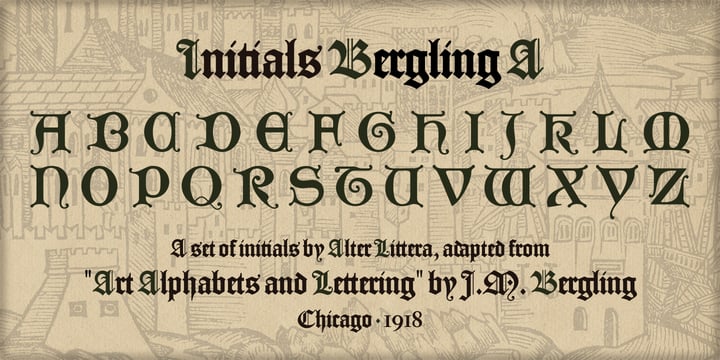
И что, спросите вы, неужели только так и не иначе? Неужели писцы всегда придерживались рамок определенного шрифта?
Шрифты букв в средневековом стиле — Последователи ▷➡️
Письменные шрифты в средневековом стиле.
к открывать разные источники для Instagram откройте платформу, напишите или вставьте свой контент, просмотрите его в разных макетах, скопируйте отрывок с нужным шрифтом и вставьте текст в Instagram, Facebook, Twitter, Youtube, WhatsApp, Twitch, TikTok или любая социальная сеть. Есть и другие места, которые также предлагают эту услугу.
Поскольку Instagram Stories предлагает некоторые возможности, когда мы пишем описания, комментарии или сообщения, нет возможности, кроме шрифта по умолчанию.
Несмотря на это, есть сторонние приложения которые предлагают пользователям возможность размещать другие источники. Продолжайте с нами, чтобы узнать больше об этой альтернативе и узнать, как применять шрифты, которые делают ваши публикации более привлекательными, в данном случае шрифты в средневековом стиле.
У Followers Online очень простая страница, вам просто нужно напишите свой текст чтобы узнать, как обстоят дела с пользовательскими шрифтами.
Позже, просто скопируйте и вставьте в его Instagram.